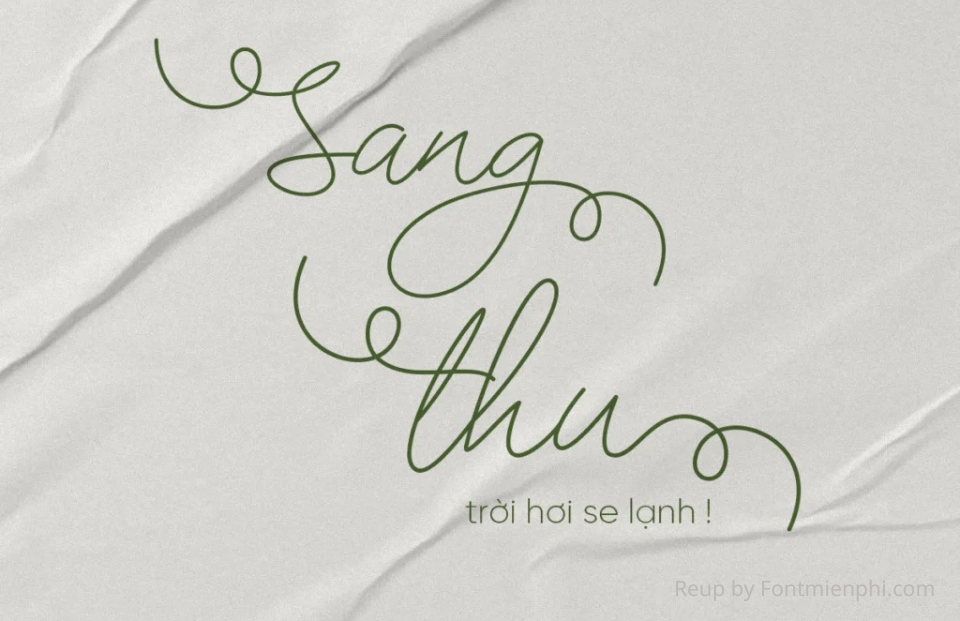
Font VL Agile Script Line Việt Hóa – Giải Pháp Thiết Kế Từ Font Miễn Phí
Font Miễn Phí xin giới thiệu đến bạn VL Agile Script Line – một bộ font Việt hóa mang đậm phong cách chữ ký và viết tay. Sở hữu đường nét thanh mảnh cùng độ lơi bay bổng tựa như nét bút thật, đây chính là “mảnh ghép” hoàn hảo giúp các bản thiết kế của bạn trở nên nghệ thuật và mang đậm dấu ấn cá nhân.
Ứng Dụng & Ưu Điểm Nổi Bật Font VL Agile Script Line Việt Hóa
Được đánh giá là một trong những font chữ dễ thao tác nhất tại hệ thống của Font Miễn Phí, VL Agile Script Line sở hữu nhiều ưu điểm:
• Ứng dụng đa năng: Lựa chọn số 1 cho các ấn phẩm như thiết kế thiệp, lời mời, logo thương hiệu, hoặc các ghi chú chữ ký sang trọng.
• Tối ưu thẩm mỹ: Nét chữ đẹp, tự do và vô cùng dễ dàng trong việc tùy chỉnh kích thước mà không làm mất đi form dáng chuẩn của chữ.
Bí Quyết Sử Dụng Font Hiệu Quả Font VL Agile Script Line Việt Hóa
• Sự đồng điệu: Đảm bảo phong cách bay bổng của font phù hợp với tổng thể thiết kế (concept) và màu sắc thương hiệu.
• Tỷ lệ hợp lý: Luôn căn chỉnh kích thước phông chữ sao cho vừa vặn. Kích thước quá nhỏ sẽ làm mất đi nét thanh mảnh, gây khó đọc.